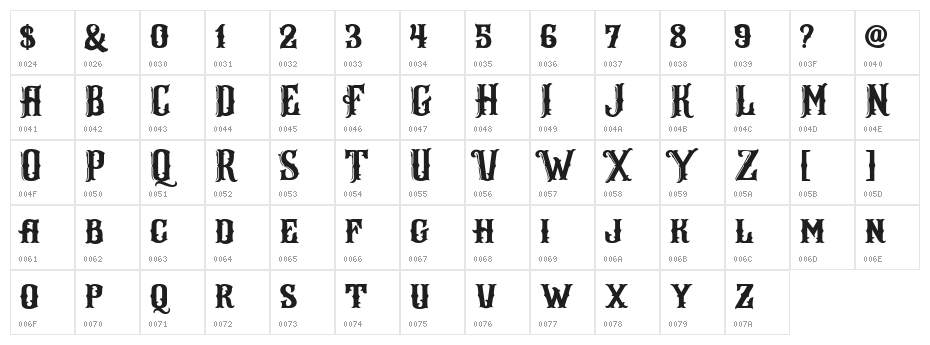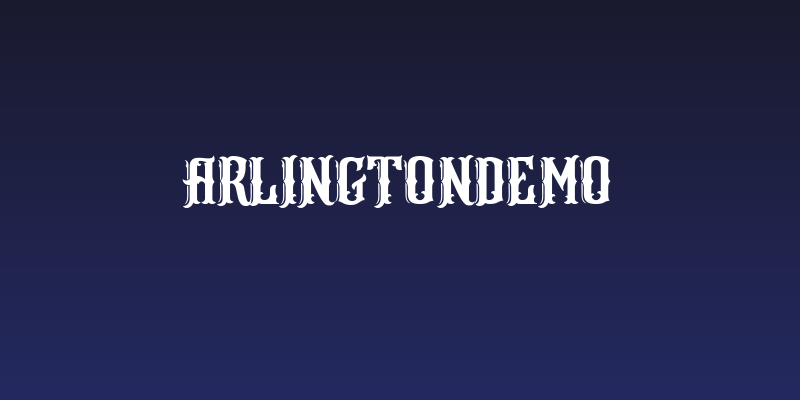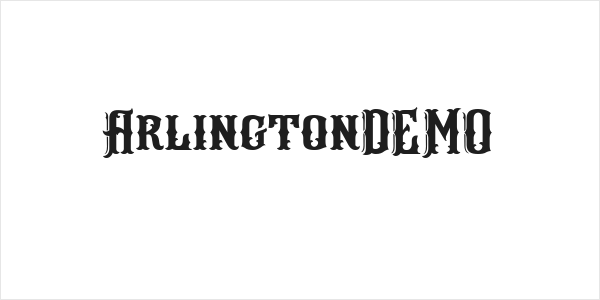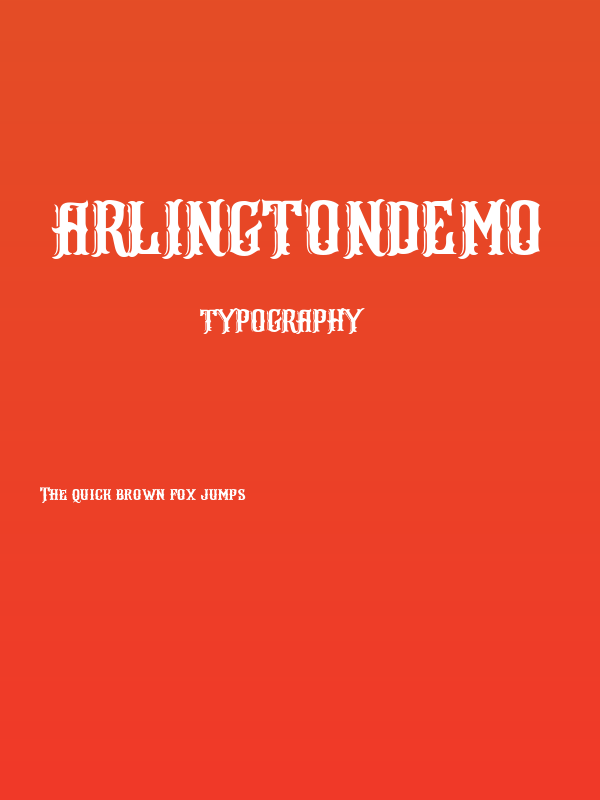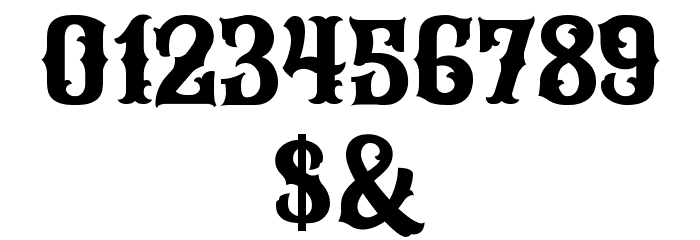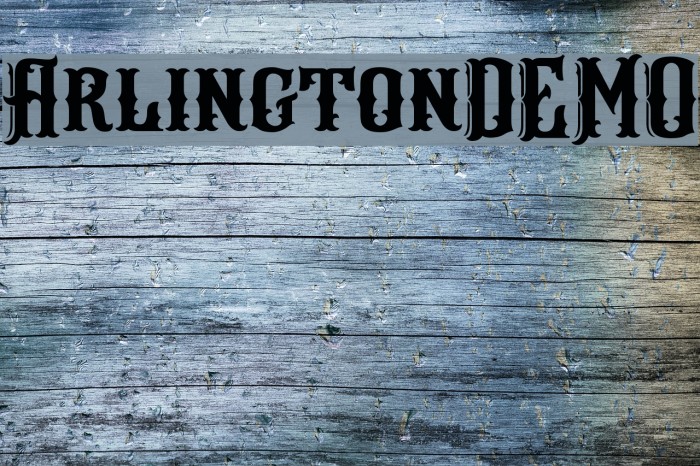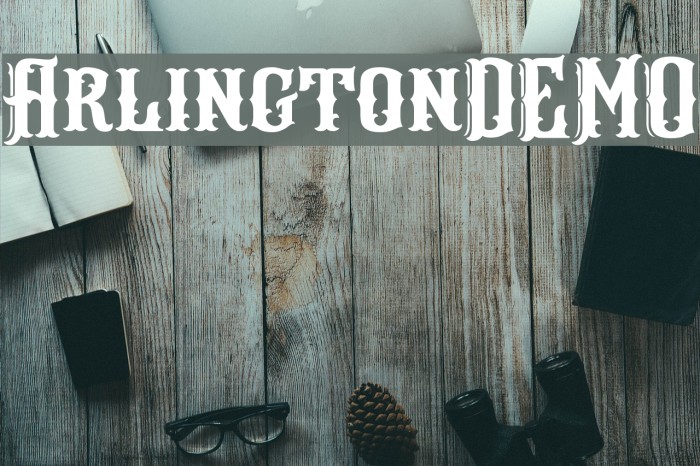
ArlingtonDEMO Font
| Estilo general | Vintage |
| Proyectos propuestos | Ideal for posters, logos, branding, and any design needing a vintage or Western theme. |